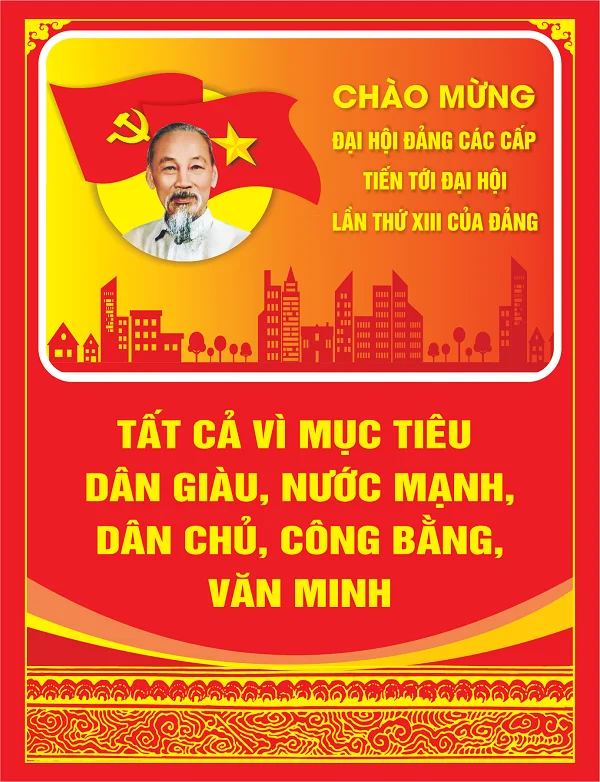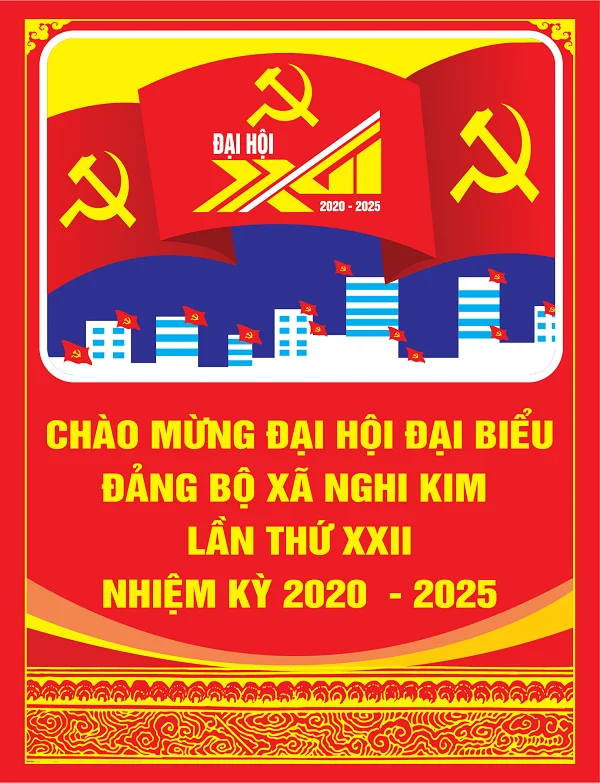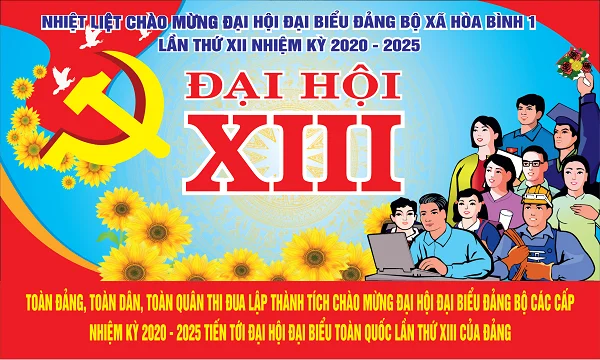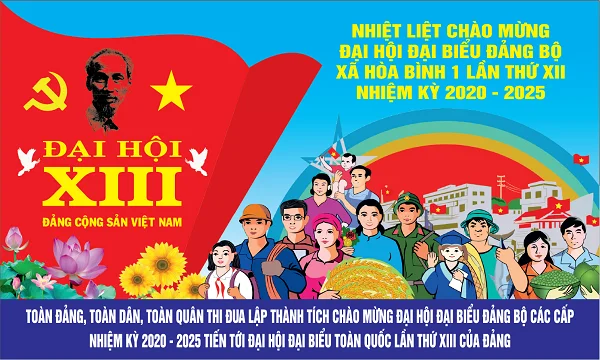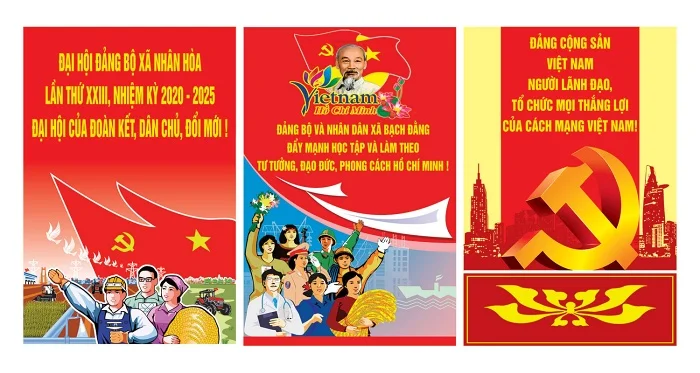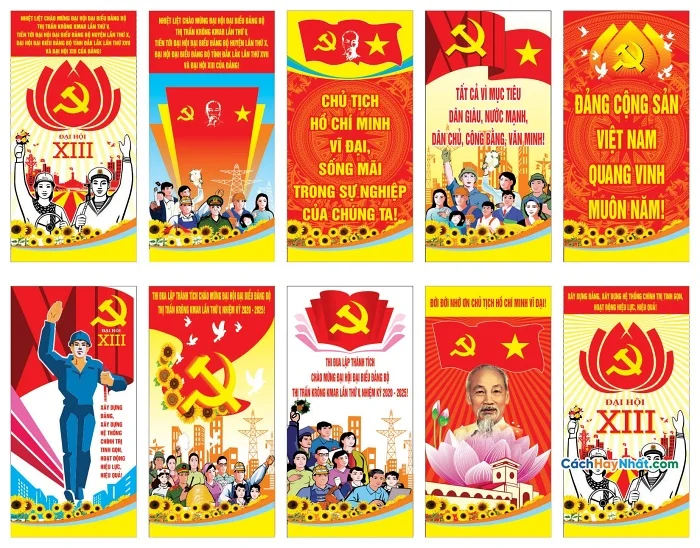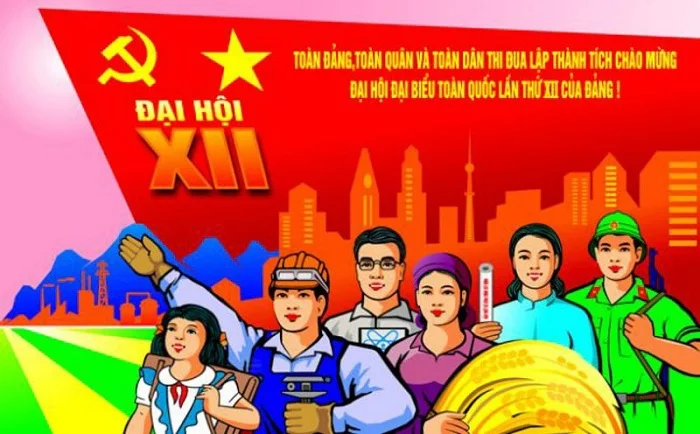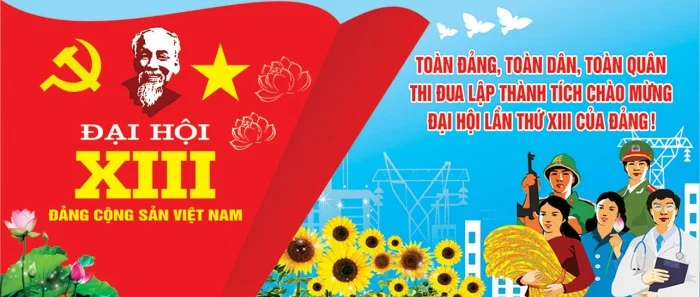
Đại hội Đảng do Ban Chấp hành Trung ương triệu tập thường lệ 5 năm 1 lần, theo Điều lệ là "cơ quan lãnh đạo cao nhất của Đảng". Đại biểu dự đại hội gồm các Ủy viên Ban Chấp hành Trung ương triệu tập đại hội và đại biểu do đại hội cấp dưới bầu. Ðại biểu chính thức dự Đại hội đại biểu toàn quốc gồm các Ủy viên Ban Chấp hành Trung ương và Đại biểu do Đại hội cấp dưới bầu; Ðại biểu dự Đại hội phải được Đại hội thẩm tra tư cách và biểu quyết công nhận. Ngày 18-2, Ban Tuyên giáo Trung ương đã ban hành Kế hoạch số 369-KH/BTGTW về tuyên truyền đại hội đảng bộ các cấp và Đại hội đại biểu toàn quốc lần thứ XIII của Đảng.
Khác với các sản phẩm in ấn khác, font chữ trên băng rôn khẩu hiệu chào mừng Đại hội Đảng toàn quốc cần phải đặc biệt lưu ý.
Font chữ được coi là linh hồn cho các ấn phẩm quảng cáo, truyền thông, tuyên truyền. Khi lựa chọn font chữ cho ấn phẩm tuyên truyền Đại hội Đảng cần đề cao tiêu chí:
Các font chữ cổ điển luôn được ưu tiên lựa chọn, nét chữ cứng nhắc vừa đủ, hạn chế sử dụng hiệu ứng 3D và đổ bóng.
Bên cạnh đó việc lựa chọn màu sắc cho font chữ cũng cần quan tâm. Vàng và đỏ là hai màu sắc chủ đạo luôn được ưu tiên lựa chọn.
Đảng Cộng sản Việt Nam - Người lãnh đạo, tổ chức mọi thắng lợi của cách mạng Việt Nam!
Phát huy sức mạnh tổng hợp của cả hệ thống chính trị và nền văn hóa, con người Việt Nam để phát triển đất nước!
Kiên định và vận dụng, phát triển sáng tạo chủ nghĩa Mác - Lênin, tư tưởng Hồ Chí Minh!
Kiên định mục tiêu độc lập dân tộc và chủ nghĩa xã hội.
Kiên định đường lối đổi mới của Đảng!
Giữ vững bản chất giai cấp công nhân của Đảng, kiên định các nguyên tắc xây dựng Đảng!
Phát triển kinh tế - xã hội là trung tâm; xây dựng Đảng là then chốt; phát triển văn hóa là nền tảng tinh thần; bảo đảm quốc phòng, an ninh là trọng yếu, thường xuyên!
Phát huy ý chí và sức mạnh đại đoàn kết toàn dân tộc kết hợp với sức mạnh thời đại để xây dựng và bảo vệ vững chắc Tổ quốc Việt Nam xã hội chủ nghĩa!
Đảng vững mạnh, Đất nước phát triển, Dân tộc trường tồn!
Dân tộc cường thịnh, trường tồn - Đất nước phồn vinh, hạnh phúc!
Đẩy mạnh toàn diện, đồng bộ công cuộc đổi mới, công nghiệp hóa, hiện đại hóa đất nước!
Kết hợp chặt chẽ giữa phát triển bền vững kinh tế biển với bảo đảm quốc phòng, an ninh, bảo vệ chủ quyền biển, đảo, tài nguyên, môi trường biển!
Nâng cao năng suất, chất lượng, hiệu quả và sức cạnh tranh của nền kinh tế!
Xây dựng đô thị hiện đại, văn minh, đô thị thông minh có bản sắc về kiến trúc và văn hóa!
Phát triển nông nghiệp, kinh tế nông thôn gắn với xây dựng nông thôn mới!
Nông nghiệp sinh thái, nông thôn hiện đại, nông dân văn minh!
Toàn dân đoàn kết xây dựng nông thôn mới, đô thị văn minh!
Nông thôn mới, sức sống mới, diện mạo mới!
Hoàn thiện toàn diện, đồng bộ thể chế, phát triển kinh tế thị trường định hướng xã hội chủ nghĩa!
Xây dựng nền kinh tế độc lập, tự chủ; nâng cao hiệu quả hội nhập kinh tế quốc tế!
Chuyển đổi số quốc gia, phát triển kinh tế số, xây dựng xã hội số!
Khẩu hiệu tuyên truyền về xây dựng và phát huy giá trị văn hóa, sức mạnh con người việt nam
Văn hóa là nền tảng tinh thần, nguồn lực nội sinh và động lực đột phá cho phát triển kinh tế - xã hội và hội nhập quốc tế!
Giá trị văn hóa, con người Việt Nam là nền tảng, sức mạnh nội sinh quan trọng bảo đảm sự phát triển bền vững!
Phát triển con người toàn diện và xây dựng nền văn hóa Việt Nam tiên tiến, đậm đà bản sắc dân tộc!
Tài năng, trí tuệ, phẩm chất của con người Việt Nam là trung tâm, mục tiêu và động lực phát triển quan trọng nhất của đất nước!
Xây dựng con người Việt Nam thời đại mới, gắn kết chặt chẽ, hài hòa giữa giá trị truyền thống và giá trị hiện đại!